デザインとフォントは切っても切り離せない関係です。
毎回フォントを探すのに時間をかけすぎてしまうなんてこともしばしば…(探すのが楽しかったりもする)
いつもイメージを絞ってフォントを選んでいますが、今日は温かみがある・可愛らしいフォントを選んでみました。
温かみがある・可愛いフォントはどんな場面で使われるか。
この場合は視認性よりデザインのイメージに寄せることを重視するので、じっくり読んでほしいようなビジネス寄りの場面では使いにくいと思います。
例えば子供向けのチラシやカフェのメニューなどに重宝されそうですね。
ふわふで
筆圧の強弱がはっきりした墨っぽいフォントです。
優しくふわふわしているのでパンケーキのメニューとかに合いそうです。
ほそふわフォント
手書きの細ペンで書いたようなすっきりとしたフォントです。
正方形のしっかりした形なので、手書きでも視認性は高いと思います。
ふんわりラウンド
ぷっくりとした極太のフォントです。
丸みがあるので、ミニマルに使うとおしゃれで可愛らしくなると思います。
花とちょうちょ
流れるような手書き文字でカジュアル感のあるフォントです。
女性っぽいイメージがあり、コスメのPOPとかレビューコメントに合いそうです。
おもてなし明朝
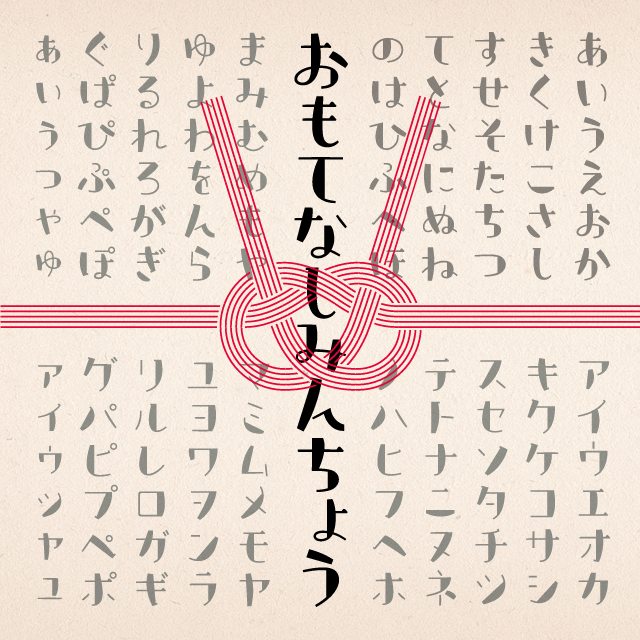
おもてなし明朝
和風でレトロ感のある一味あるフォントです。
大正ロマン的なデザインや観光マップとかに合いそうです。
KFひま字モコ
文字のキワがモコモコした可愛いフォントです。
子ども向けや動物関係のチラシに合いそうです。(うさぎふれあいパーク的な)
ぱぐのみんちょ
ぽてっとしたクリームみたいなフォルムのフォントです。(濁点が肉球みたいで可愛い)
少しレトロ感もあるので、喫茶店のチラシとかに合いそうです。
こまどり
はらいが特徴的なサッパリとしたフォントです。
小鳥をイメージして作成されているようで、夏の爽やかなデザインに合いそうです。
りいもなか
角マーカーで書いたような太字フォントです。
楽しそうなイメージもあるので、親子向けのイベントチラシに合いそうです。
やさしさゴシック
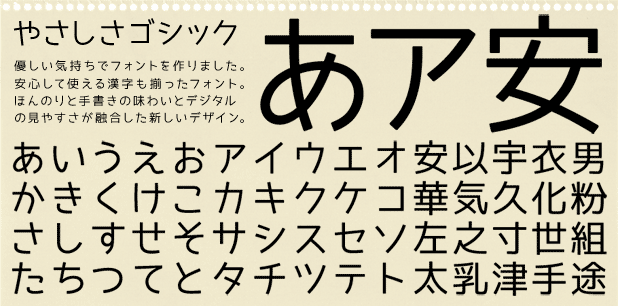
やさしさゴシック
視認性もありつつ親しみやすいフォントなので、色んな場面で使いやすそうです。
以上、温かみのある可愛い日本語フォント10選を紹介しました。